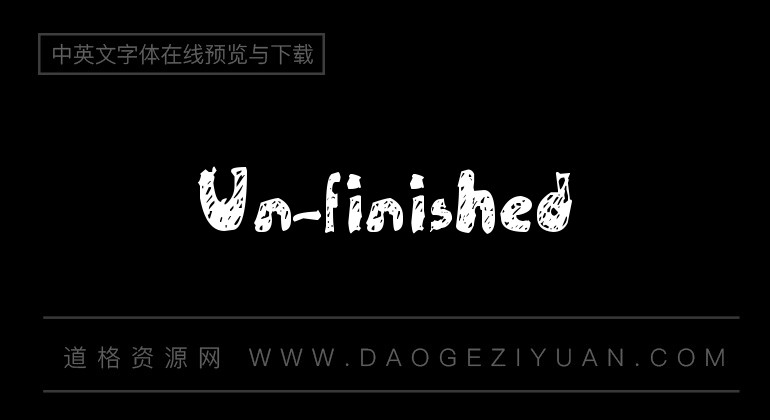
Un-finished
Un-finished 是一款由荷兰设计师 Jeroen van Eerden 创作的字体。它是一款抽象、抽象的字体,具有极其独特的设计风格。Un-finished 字体的笔画具有不完整的特点,使它看起来有着粗犷的感觉。它的字形设计极具创意,即使在细节处也能够体现出设计师的精巧技巧。Un-finished 字体可以用于创作各种各样的文字,有助于突出文字的重要性,并赋予文字独特的视觉效果。
Un-finished是一款非常不错的手写艺术字体,具有很好的视觉感,适合于文化类的宣传设计、商业类品牌的广告和产品包装设计以及个性化文字排版等较多场景。